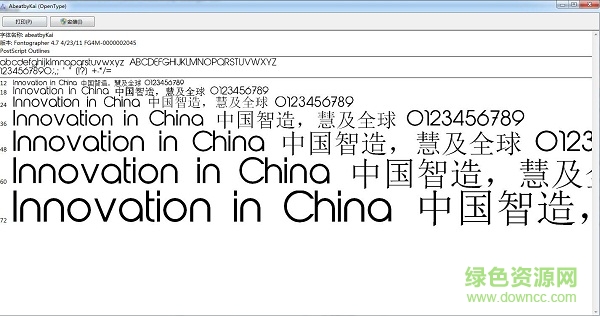
abeatbykai粗體
abeatbykai字體是一款圓勻秀美的英文字體,字體特點(diǎn)鮮明,有著出色韻律感,可以用在休閑產(chǎn)品、平面設(shè)計(jì)、時(shí)尚海報(bào)設(shè)計(jì)等方面,喜歡的朋友快來綠色資源網(wǎng)下載吧!
abeatbykai粗體